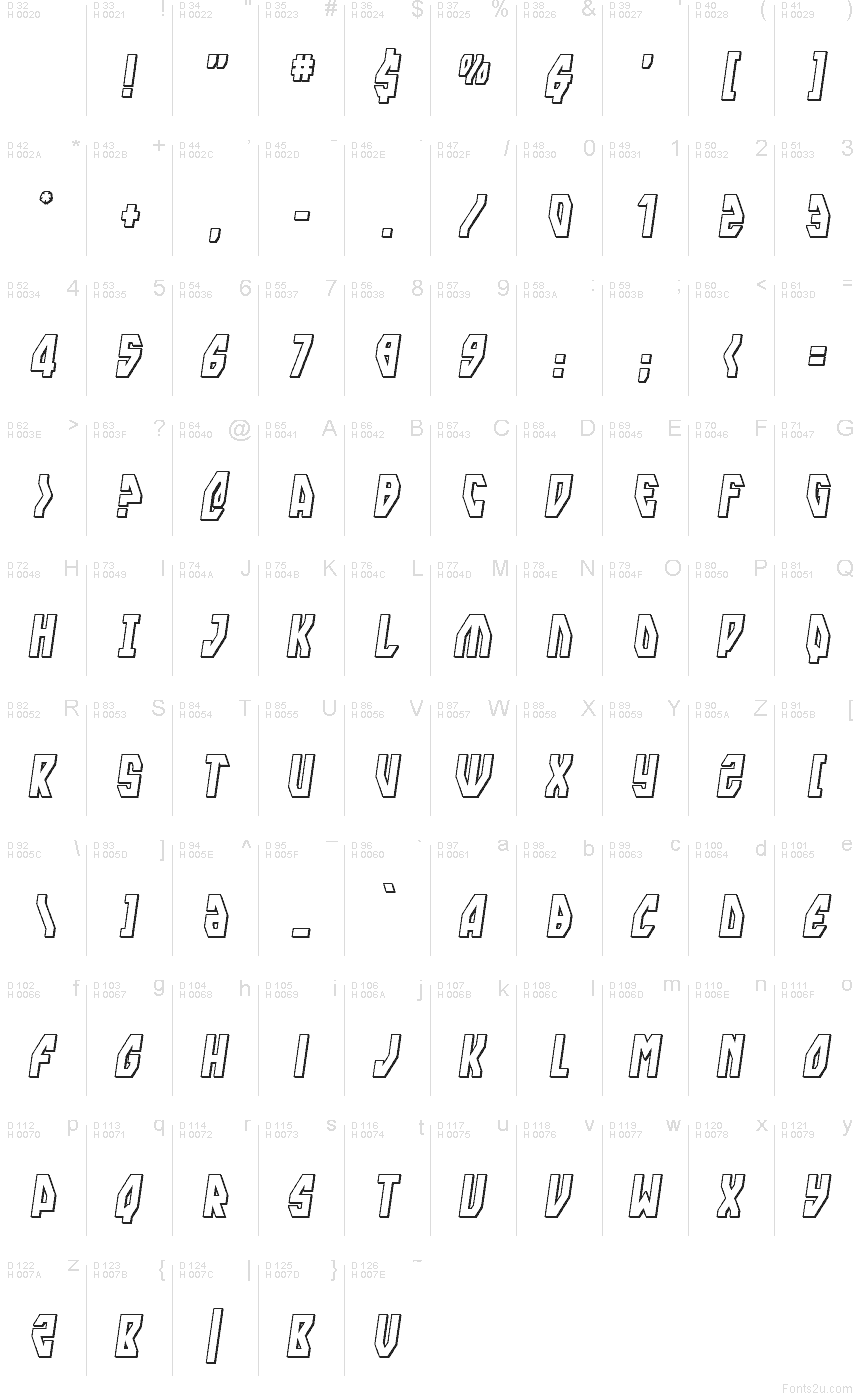
Písmo Skyrange 3D Italic od Daniela Zadoroznyho z Iconian Fonts je bezplatný techno font, který vypadá, jako by byl vyřezán z kovového plátu a pořádně rozjetý. Výrazný náklon a vrstvené, zkosené obrysy dodávají každému slovu ostrý 3D efekt, zatímco dělené tahy dodávají elegantní, technický rytmus. Působí dravě, ale přitom zůstává přehledné i při užším řádkování.
Použití Skyrange 3D Italic v herních logách, sci-fi plakátech, závodních titulech, esportových nadpisech, obalech tech produktů, náhledech videí na YouTube či letácích na akce dodá okamžitý pocit pohybu. Pro čistý kontrast jej zkombinujte s jednoduchým geometrickým bezpatkovým písmem a nechte tento bezplatný font vyniknout jako hlavní titulek. Skyrange 3D nejlépe funguje, když mu dopřejete trochu místa.